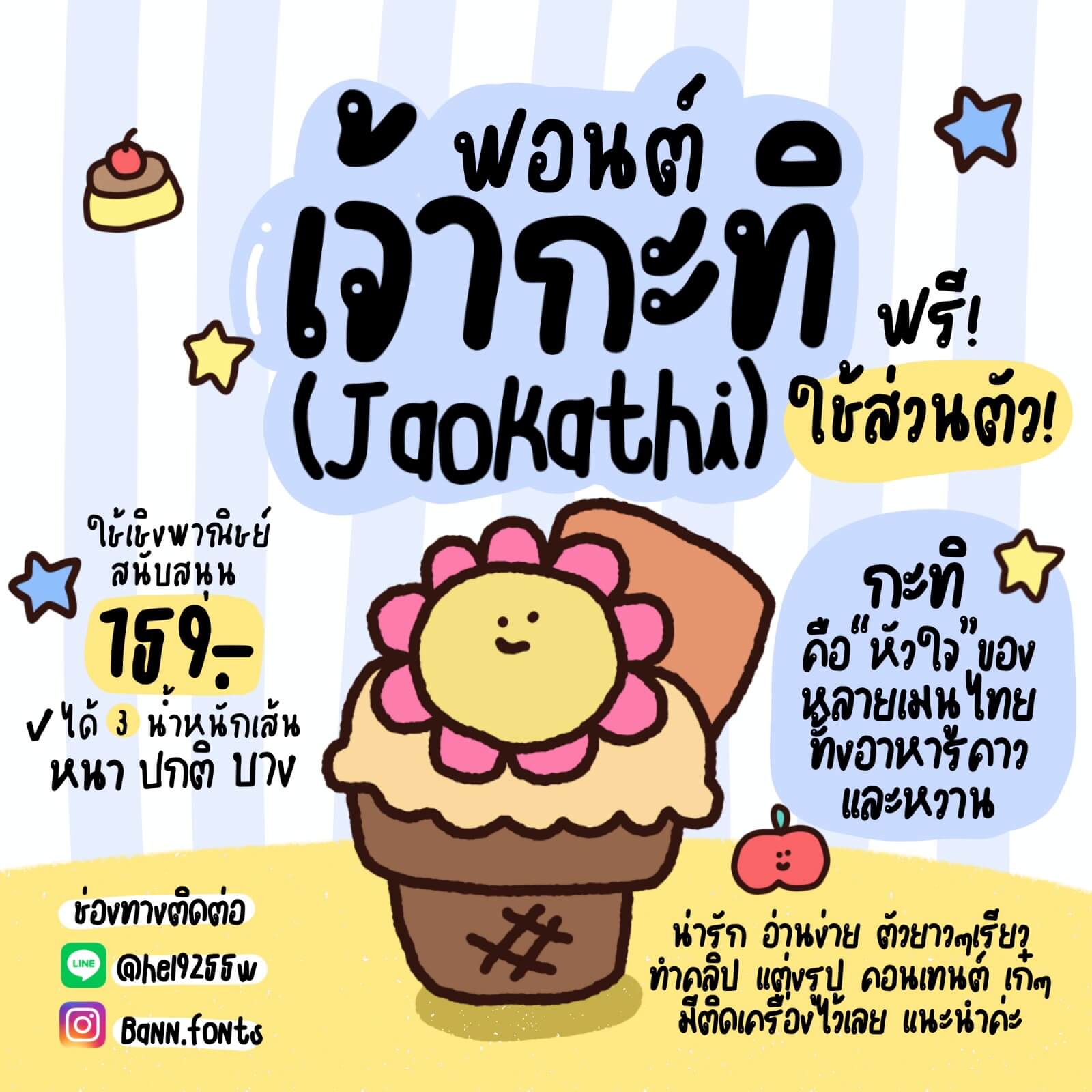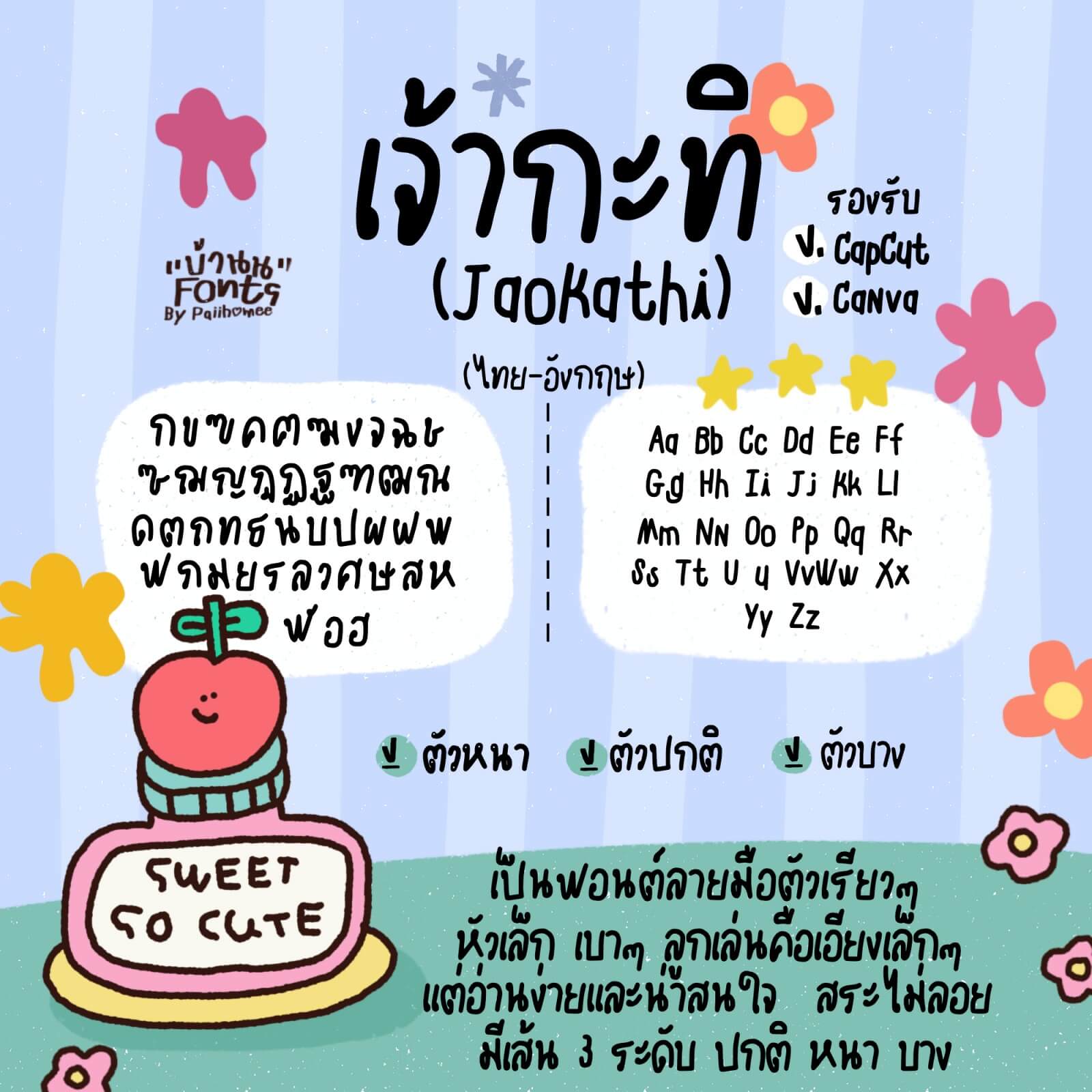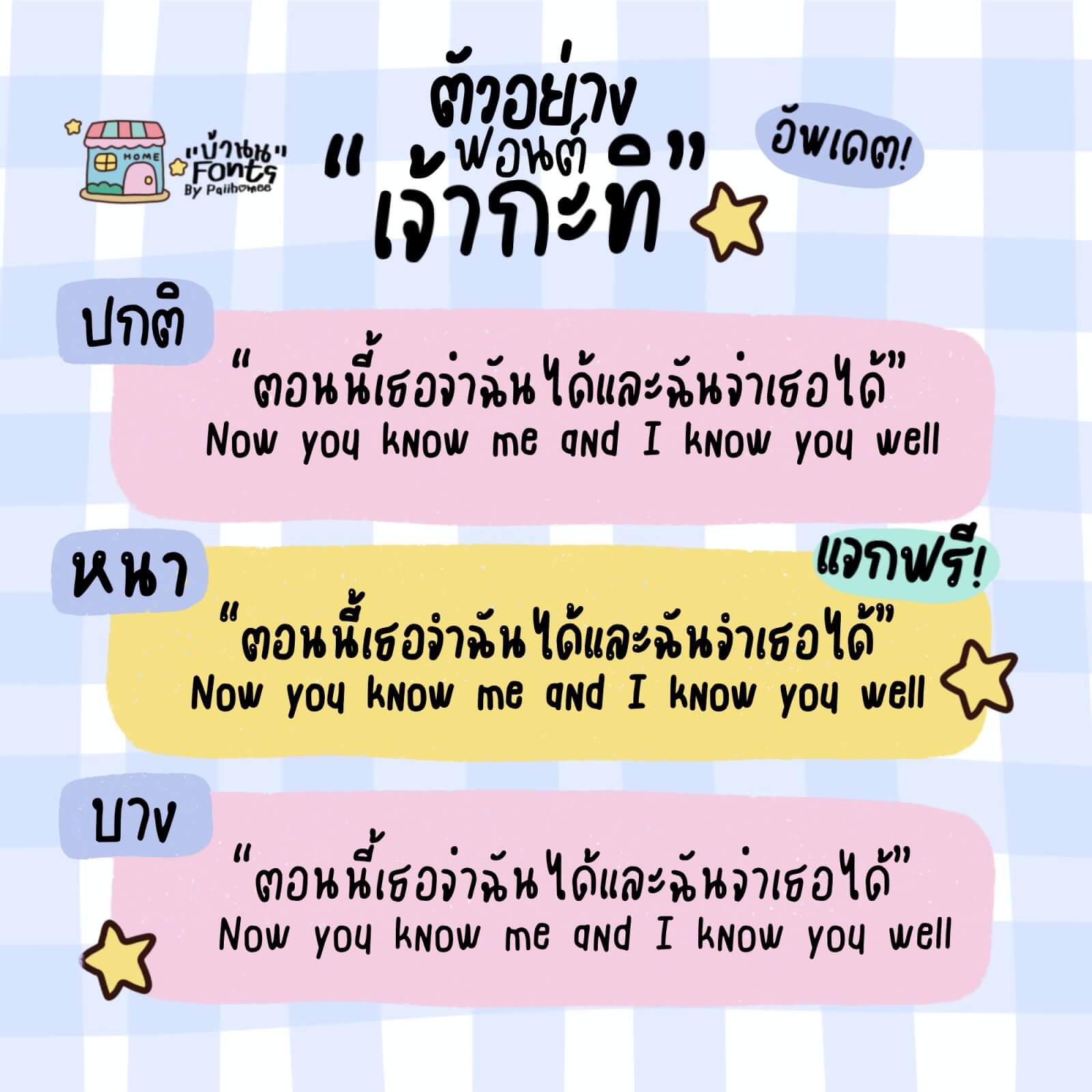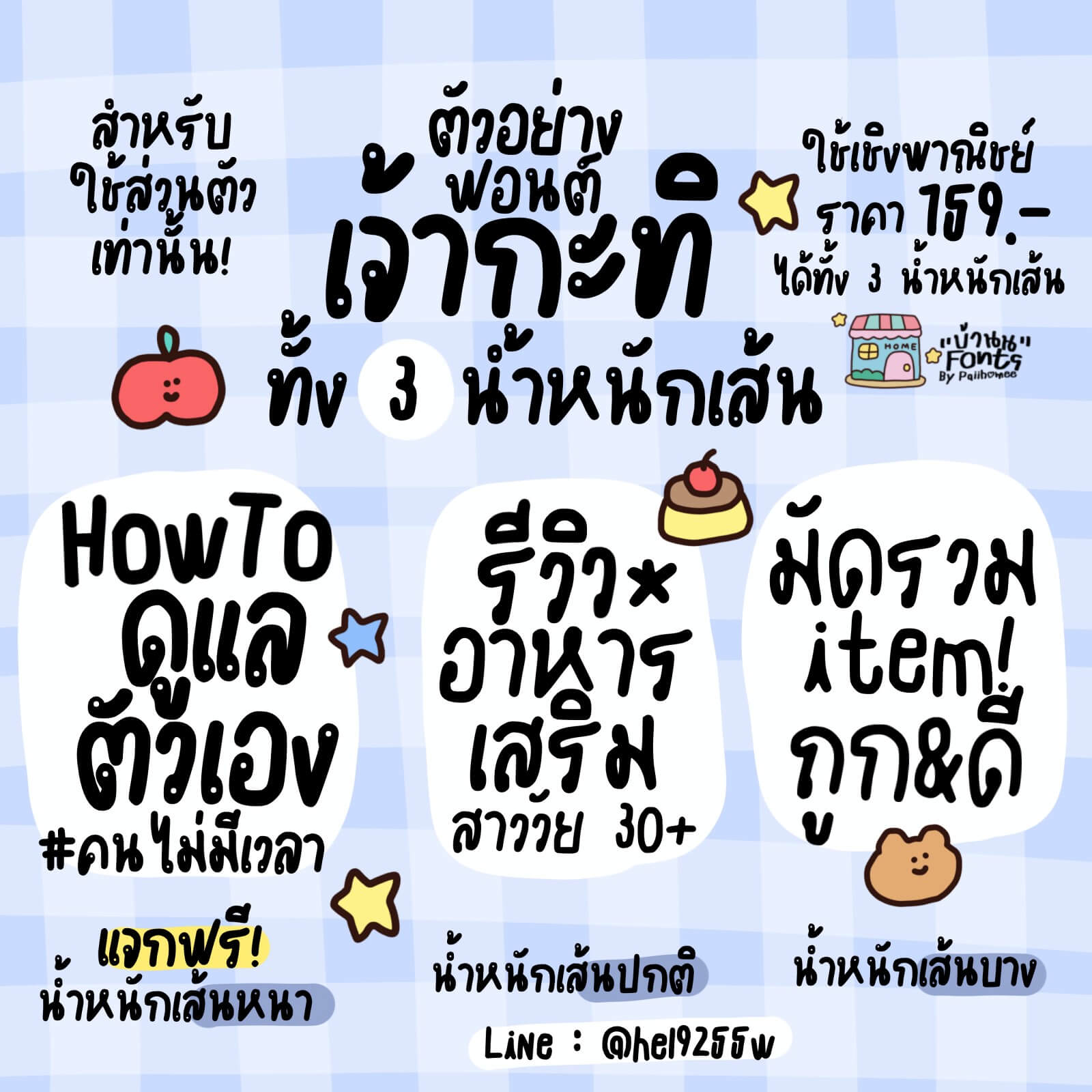
ฟอนต์เจ้ากะทิ – แจกฟรี! สำหรับใช้ส่วนตัว ฟอนต์น่ารัก อ่านง่าย ตัวยาวๆ เรียว ทำคลิป แต่งรูป คอนเทนต์ เก๋ๆ มีติดเครื่องไว้เลย แนะนำค่ะ
ไม่มีเลขไทย (๐๑๒๓๔๕๖๗๘๙)
เจ้ากะทิ (JaoKathi)